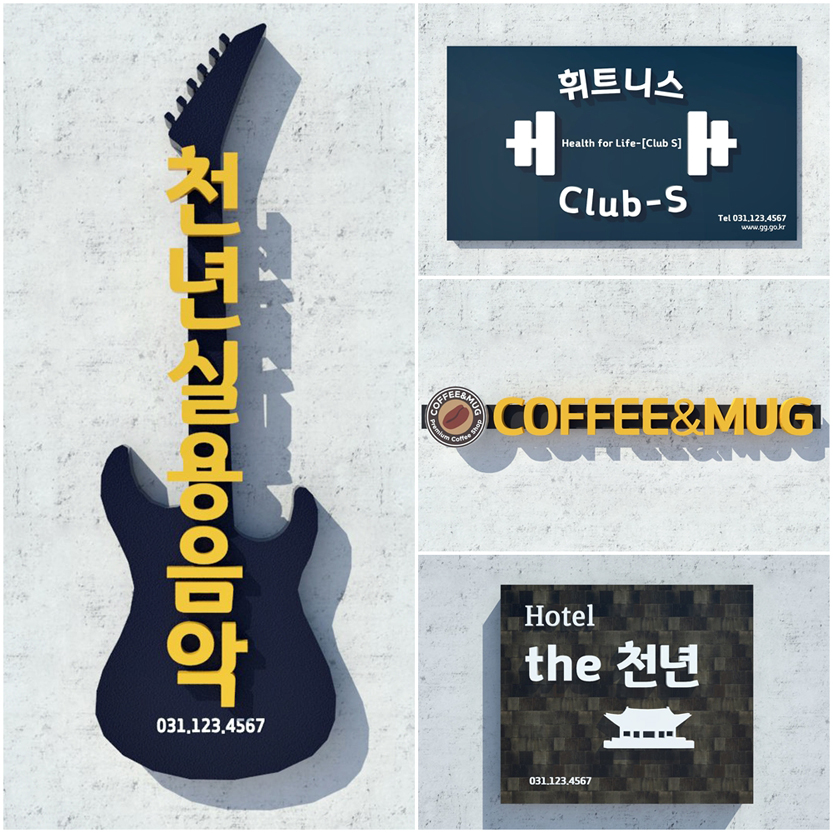
경기천년제목 — 경기도에서 배포하는 무료 폰트입니다. 한반도의 동서남북을 잇는다는 이음을 콘셉트로, 전통미를 현대적으로 풀어낸 제목용 서체
경기라는 지명이 쓰인 지 천 년이 된 것을 기념해 경기도가 만든 서체입니다. 2016년 6월부터 열 달에 걸쳐 개발해 2017년 4월에 공개했습니다.
콘셉트는 이음입니다. 경기도가 밝힌 설명에 따르면 한반도의 동서남북을 연결하는 지정학적 특성과, 다른 지역에 비해 유연하고 융통성 있는 도민의 인성을 이음이라는 개념으로 옮겼습니다. 그것이 자음과 모음의 유연한 연결, 꼭지 모양과 받침의 마무리가 위로 올라가는 형태로 조형에 반영됐습니다. 자음과 모음이 자연스럽게 이어지는 것은 협력과 포용을, 그리고 과거와 현재와 미래를 잇는다는 뜻을 나타낸다고 설명합니다.
현대 한글 11,172자를 모두 담았고 세로쓰기와 한자까지 지원합니다. 굵기는 Light와 Medium, Bold, V 네 가지입니다. 제목용으로 만들어졌고 본문은 짝을 이루는 경기천년바탕이 맡습니다. 공공누리 제1유형으로 등록돼 출처를 밝히면 상업적으로 쓸 수 있습니다.